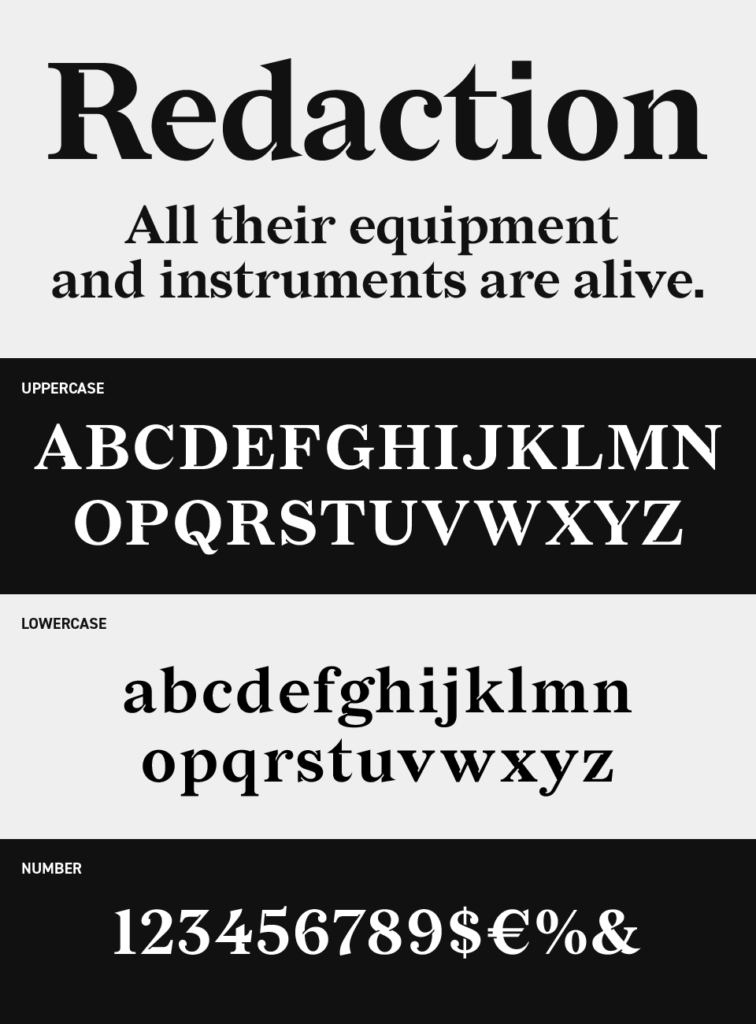
Redactionフォントは、端正なセリフ体をベースにしながら、エッジに独特のアクセントを加えた洗練された印象のセリフ体フォントです。
ちょっとした切込みなどが、細部にさりげない個性が宿り、紙面に品格をもたらすフォントです。クラシックな雰囲気を残しながらも堅苦しくなりすぎず、現代的な感覚と調和する柔軟さがあるフォントです。
フォントのウェイトやスタイルなど合計21種類用意されているので、場面に応じて使い分けも可能です。